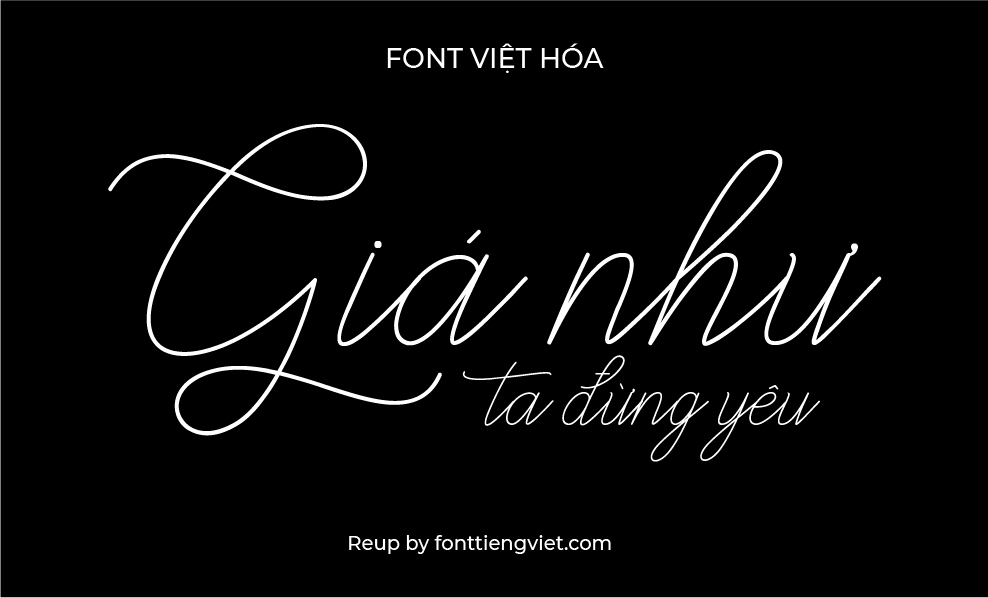
Font việt hóa MTD Abbassy Script
Giới thiệu về bộ Font việt hóa MTD Abbassy Script
Trong thế giới đồ họa hiện đại, việc tìm kiếm một bộ Font Miễn Phí có phong cách mềm mại luôn là ưu tiên hàng đầu. Font việt hóa MTD Abbassy Script là sự lựa chọn hoàn hảo cho những ai yêu thích vẻ đẹp uyển chuyển của thư pháp. Đây là một phông chữ dạng Script với những nét thanh đậm tinh tế, tạo cảm giác sang trọng và đầy tính nghệ thuật. Được đội ngũ MTD chăm chút kỹ lưỡng, bộ font này đã giải quyết triệt để lỗi gõ tiếng Việt, giúp người dùng dễ dàng ứng dụng vào các phần mềm như Photoshop hay Canva. Đối với học sinh và sinh viên, đây là công cụ đắc lực để trang trí bài giảng hoặc làm thiệp chúc mừng ý nghĩa.
Ưu điểm nổi bật của Font việt hóa MTD Abbassy Script
Thiết kế bay bổng và linh hoạt
Đặc điểm nổi bật nhất của Font việt hóa MTD Abbassy Script chính là sự kết hợp hài hòa giữa nét cổ điển và hơi thở hiện đại. Các ký tự được liên kết với nhau một cách tự nhiên, mô phỏng lại nét bút lông của những nghệ nhân viết chữ. Nhờ sự tối ưu hóa bảng mã, bạn có thể gõ các dấu câu tiếng Việt mà không lo bị nhảy lỗi ký tự lạ. Điều này cực kỳ quan trọng trong các dự án in ấn đòi hỏi sự chỉn chu cao.
Ứng dụng đa dạng trong thực tế
Bộ font này thường xuyên xuất hiện trong các thiết kế bìa sách, tiêu đề blog hoặc các ấn phẩm truyền thông của nhà trường. Với vẻ ngoài thanh thoát, nó giúp nội dung trở nên gần gũi và thu hút người xem hơn bao giờ hết.